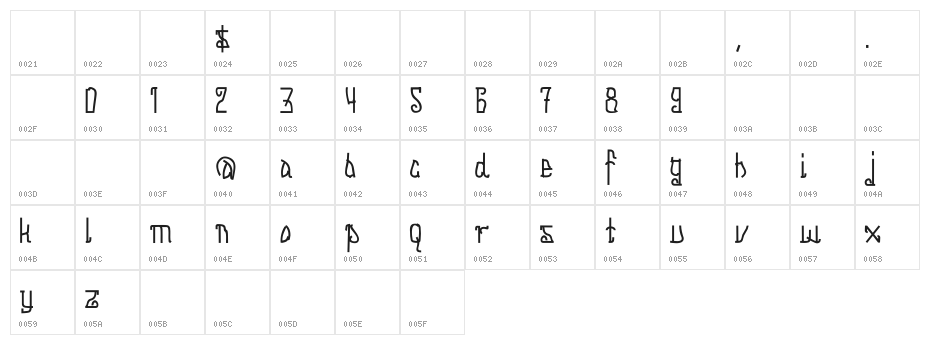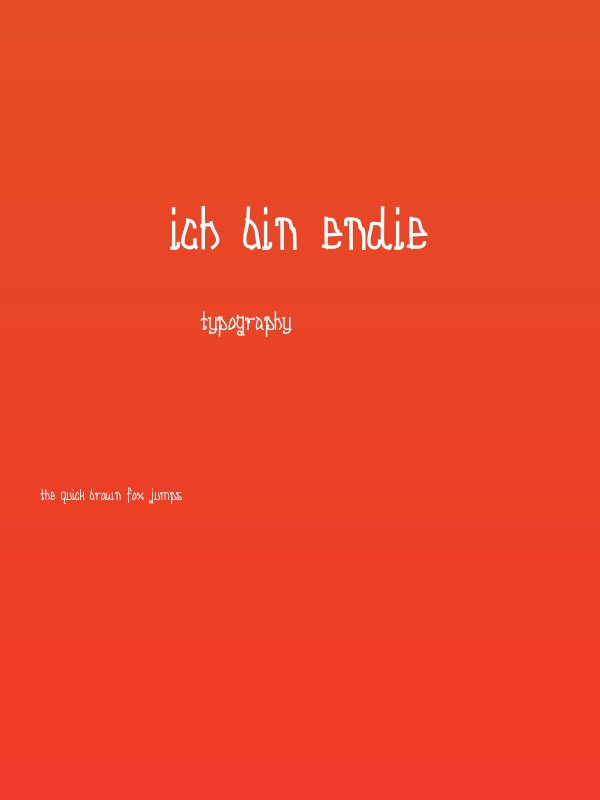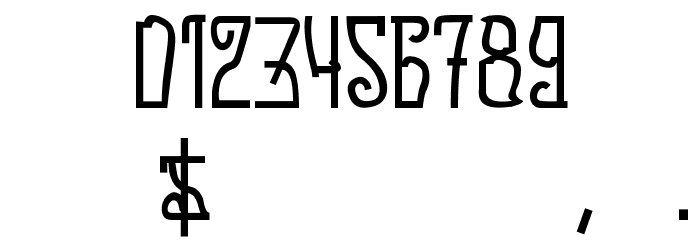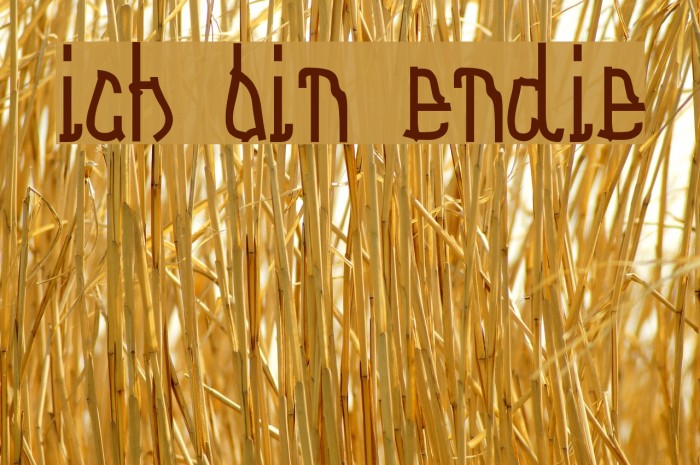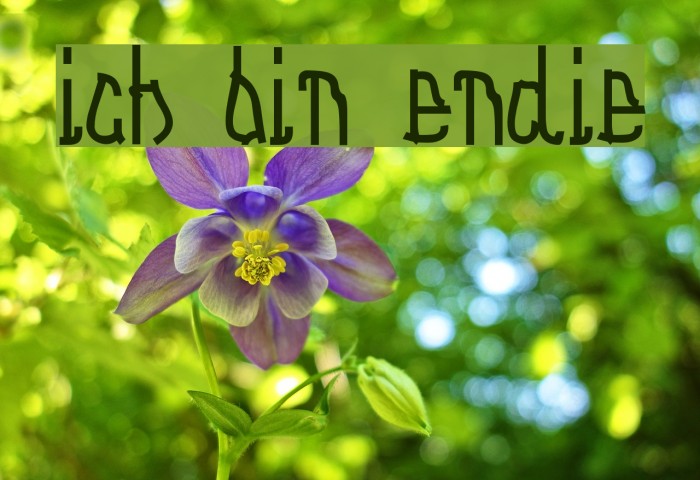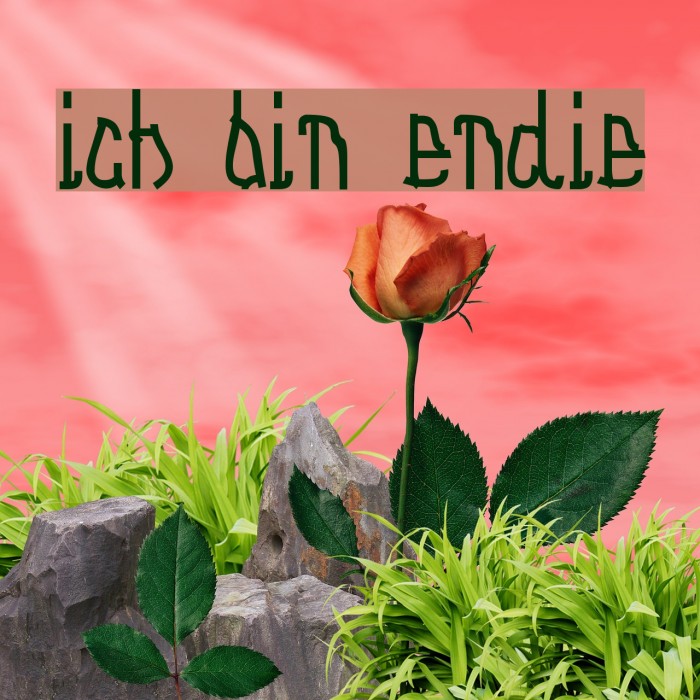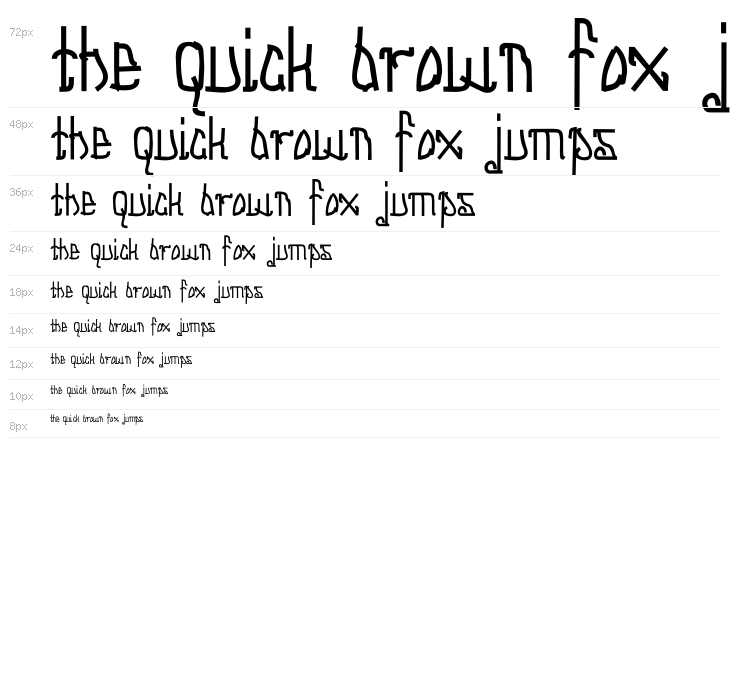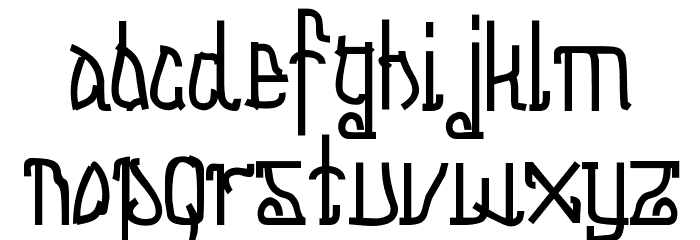
Ich bin Endie Font
✎ Quirky
| Cas d'utilisation | Logos, Posters, Creative Branding |
| Projets proposés | Ideal for creative projects such as posters, album covers, and branding materials that seek a unique and artistic flair. |